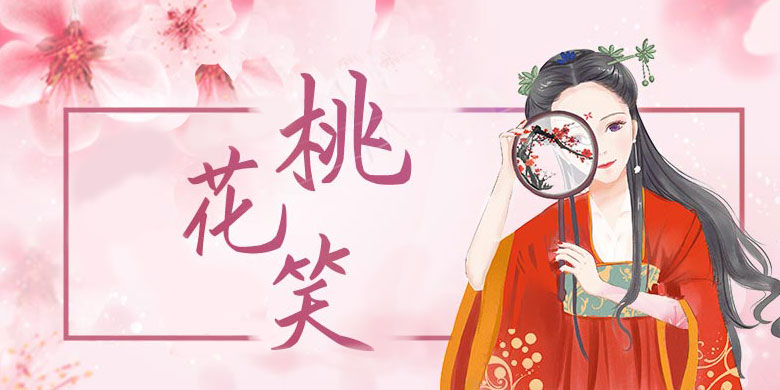
方正手迹-桃花笑
品牌:方正手迹设计师:尚正中发行时间:2020字库编码:大陆简体(GB2312-80)分类:常规书写·硬笔字体属性:精品字
桃花笑是一款中国风的手写体。这款字笔画简洁,粗细变化均匀,整体笔画舒展识别度极好。适用于文艺中国风类的书刊、品牌广告和产品包装设计,以及社交网络的个性化用字。